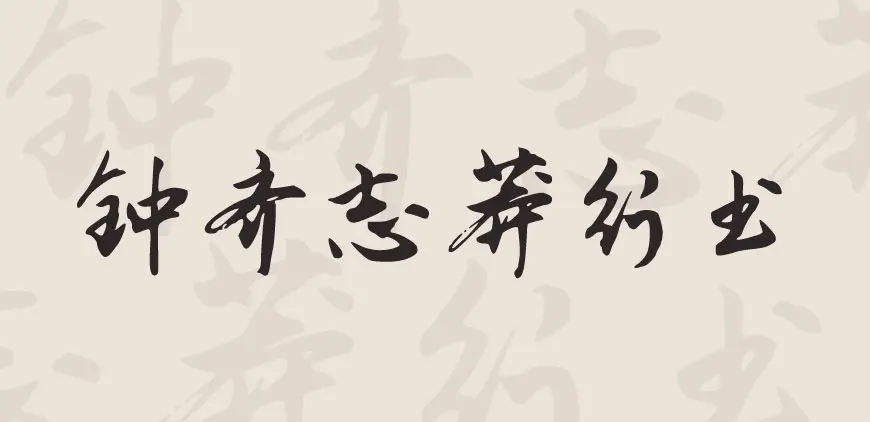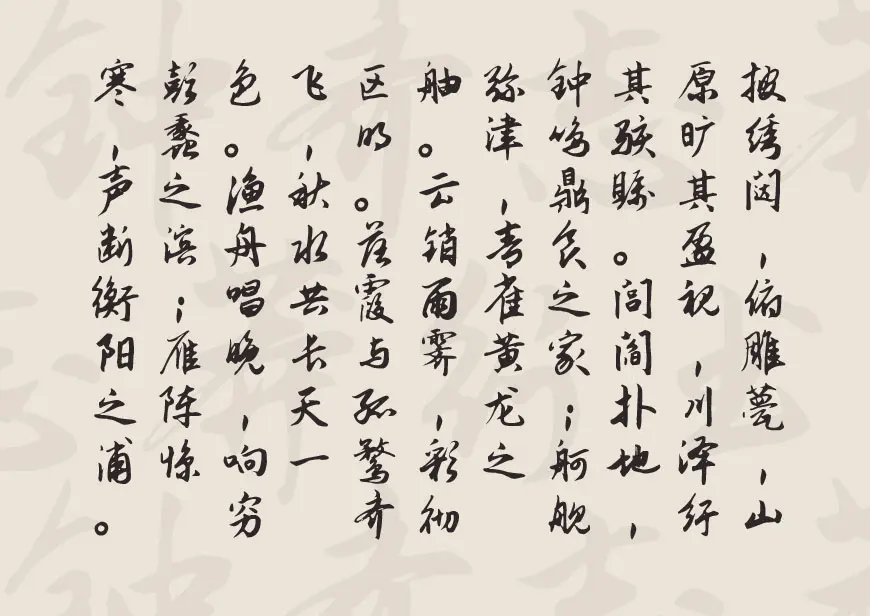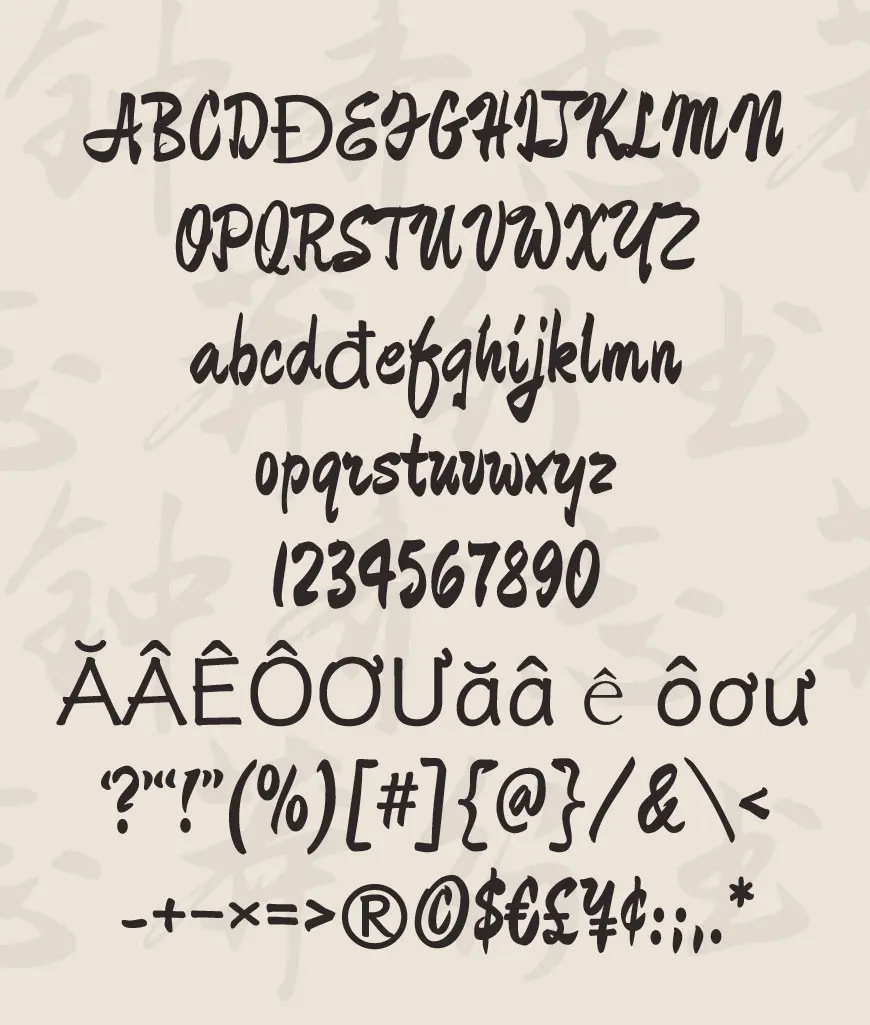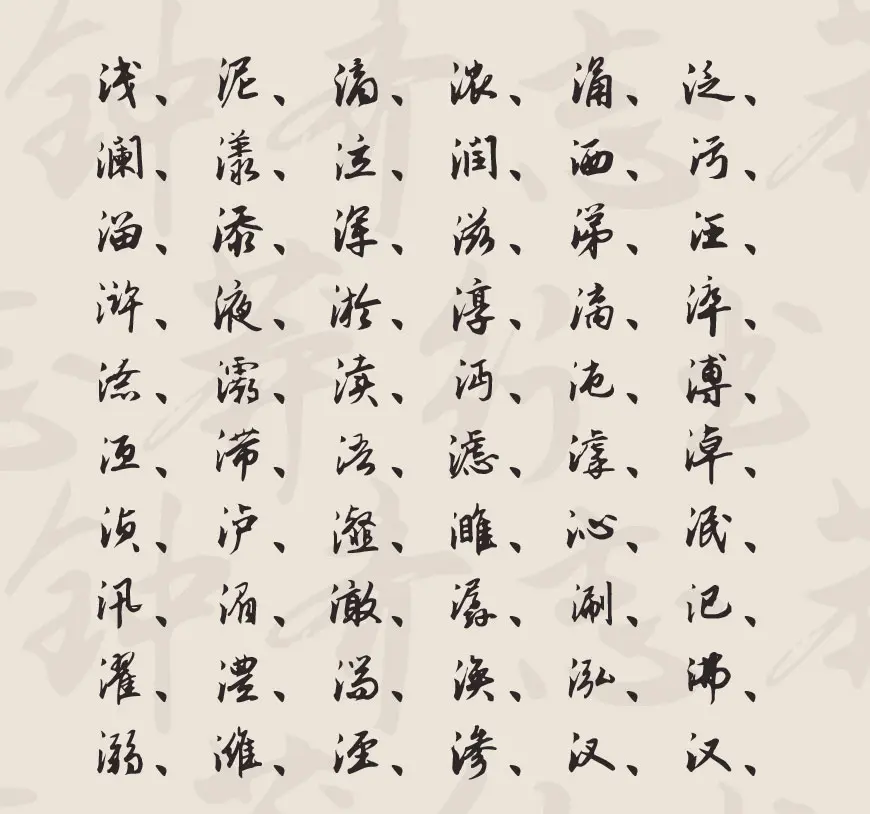
鍾齊志莽行書是谷歌開源字體項目裡的一款中文行書書法字體,遵循SIL Open Font License 1.1授權許可,由作者書法家韋志莽先生授權鍾齊字庫把這款字體上傳至Google fonts開源字體項目,志莽行書這款字體字形瀟灑飄逸,形體端秀而骨架勁挺,整體效果非常出色,鍾齊志莽行書字體可廣泛用於廣告設計、包裝設計等方面。